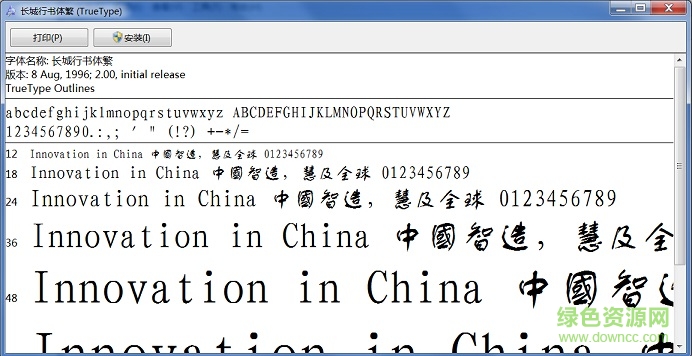
長(zhǎng)城行書(shū)體是一款非常適合用于藝術(shù)設(shè)計(jì)方面的字體,字體清晰,筆形美觀,感興趣的朋友趕緊來(lái)綠色資源網(wǎng)下載體驗(yàn)吧!
長(zhǎng)城行書(shū)字體介于楷書(shū)、草書(shū)之間的一種字體,是為了彌補(bǔ)楷書(shū)的書(shū)寫(xiě)速度太慢和草書(shū)的難于辨認(rèn)而產(chǎn)生的。